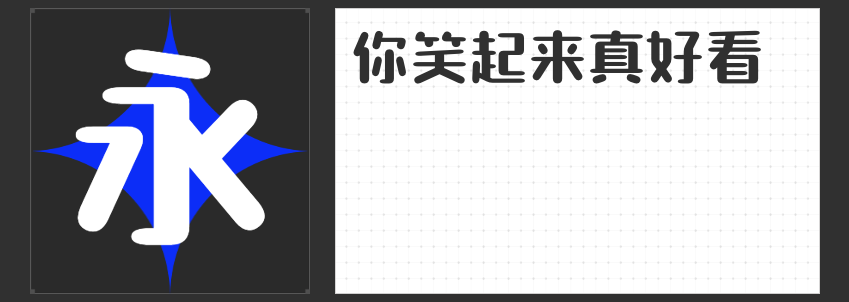
招牌设计必备:四款风格各异的店招字体推荐
在琳琅满目的商业街区,一个独特而吸引人的店招往往是吸引顾客的第一步。选择合适的字体,不仅能准确传达店铺的风格定位,还能在无形中提升品牌形象。今天,就为大家推荐四款各具特色的店招字体,助力你的店铺脱颖而出。
1.励字笑语郎朗简
这款字体以其可爱又常规的风格,成为甜美女装店铺的绝佳选择。圆润的线条搭配简洁的构造,既展现了女性的柔美与温婉,又不失品牌的专业与正规感。让顾客在第一眼就能感受到店铺的温馨与甜美。
2.喵字文案体
对于儿童服装店或宠物店而言,这款带有可爱手写感的喵字文案体无疑是最佳选择。字体的每一个笔画都仿佛充满了生命力,如同小猫的脚印一般,让人忍不住想要亲近。它不仅能够吸引小朋友的目光,也能让大人们感受到店铺的趣味与温馨。
3.励字美黑简
这款字体融合了黑体与宋体的特点,呈现出一种匀称、清秀而又不失端正的美感。它既有黑体的稳重与力量感,又保留了宋体的优雅与细腻。对于追求成熟、稳重风格的女装店铺或茶馆而言,励字美黑简无疑是提升品牌形象、彰显品牌格调的得力助手。
4.高手字斋东京体
如果你经营的是一家书店或中式餐厅,那么高手字斋东京体将是不二之选。这款字体带有浓厚的文化底蕴和复古气息,仿佛让人穿越回了那个书香四溢、韵味十足的年代。它不仅能够彰显店铺的文化底蕴和独特品味,还能吸引那些热爱传统文化、追求生活品质的顾客。
以上四款店招字体各具特色、风格迥异,但都能为店铺增添独特的魅力与风采。选择一款适合自己店铺风格的字体吧!让它在繁忙的商业街区中脱颖而出,成为顾客眼中最亮的那颗星。